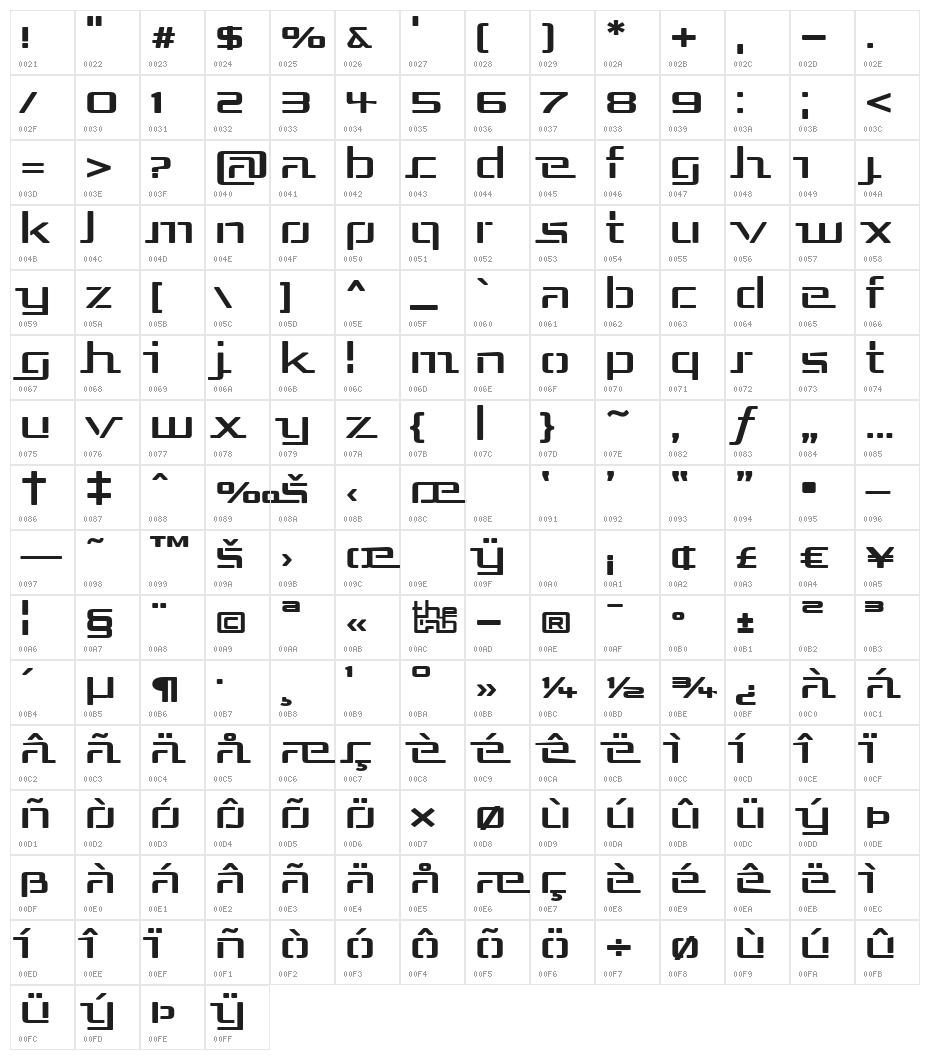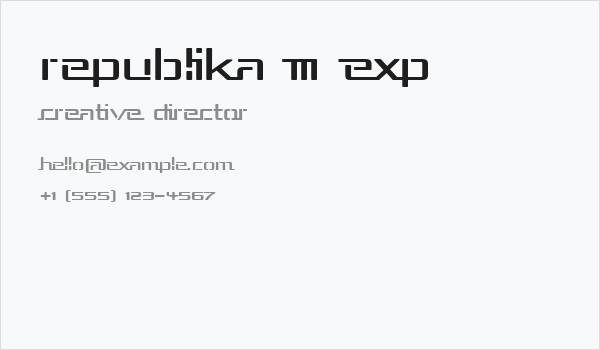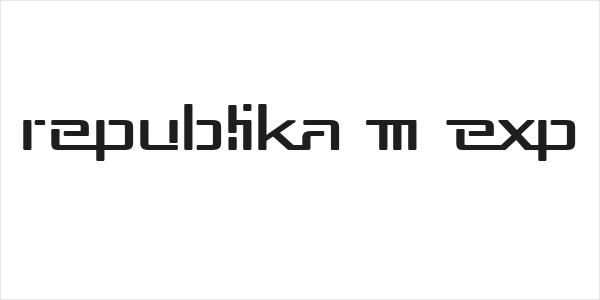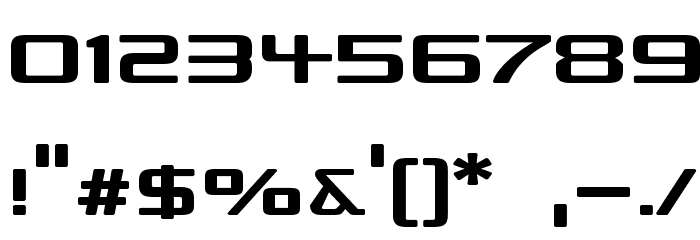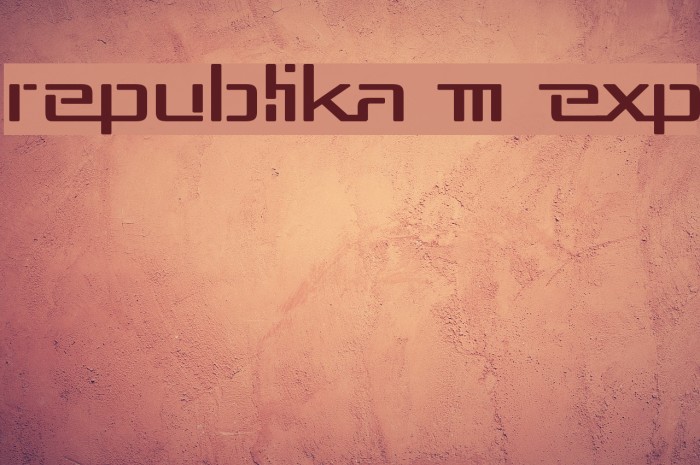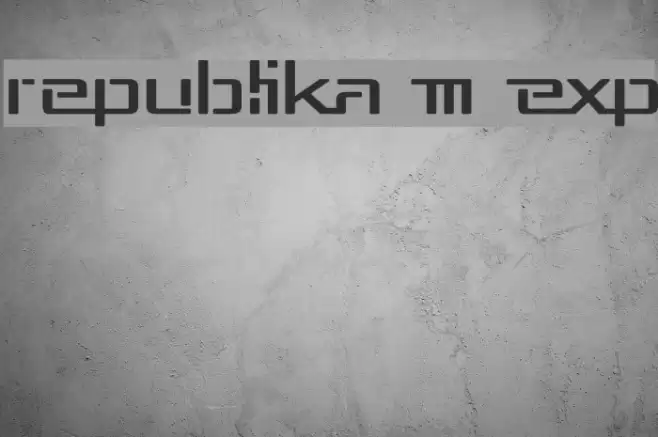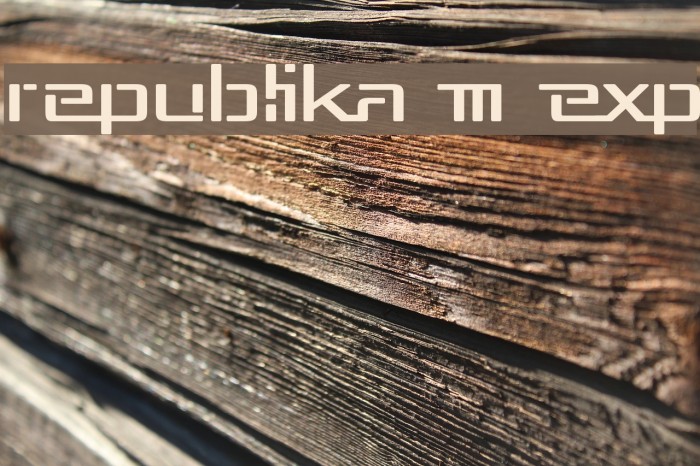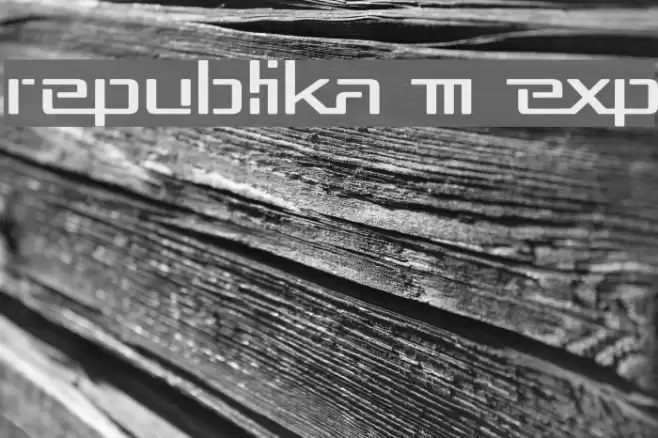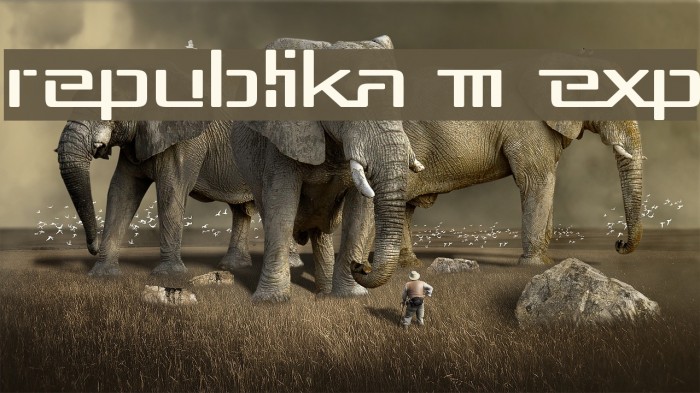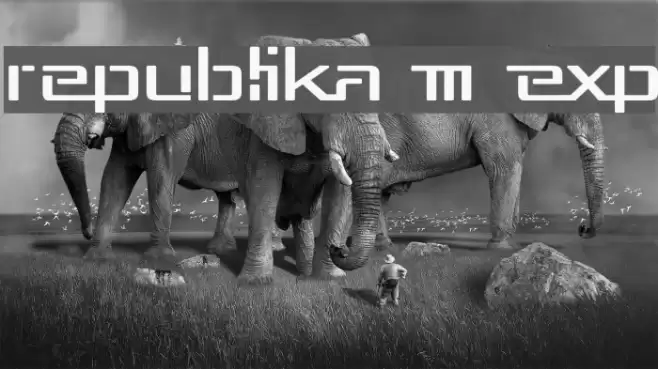
Republika III Exp Font
Fonts by Apostrophic Lab
| Categorie | Sci-fi |
| Caso d'uso | Logos, Headlines, Digital interfaces |
| Progetti proposti | Ideal for technology branding, video game design, sci-fi themed projects, and digital interfaces. |
| Autore | Fonts by Apostrophic Lab |